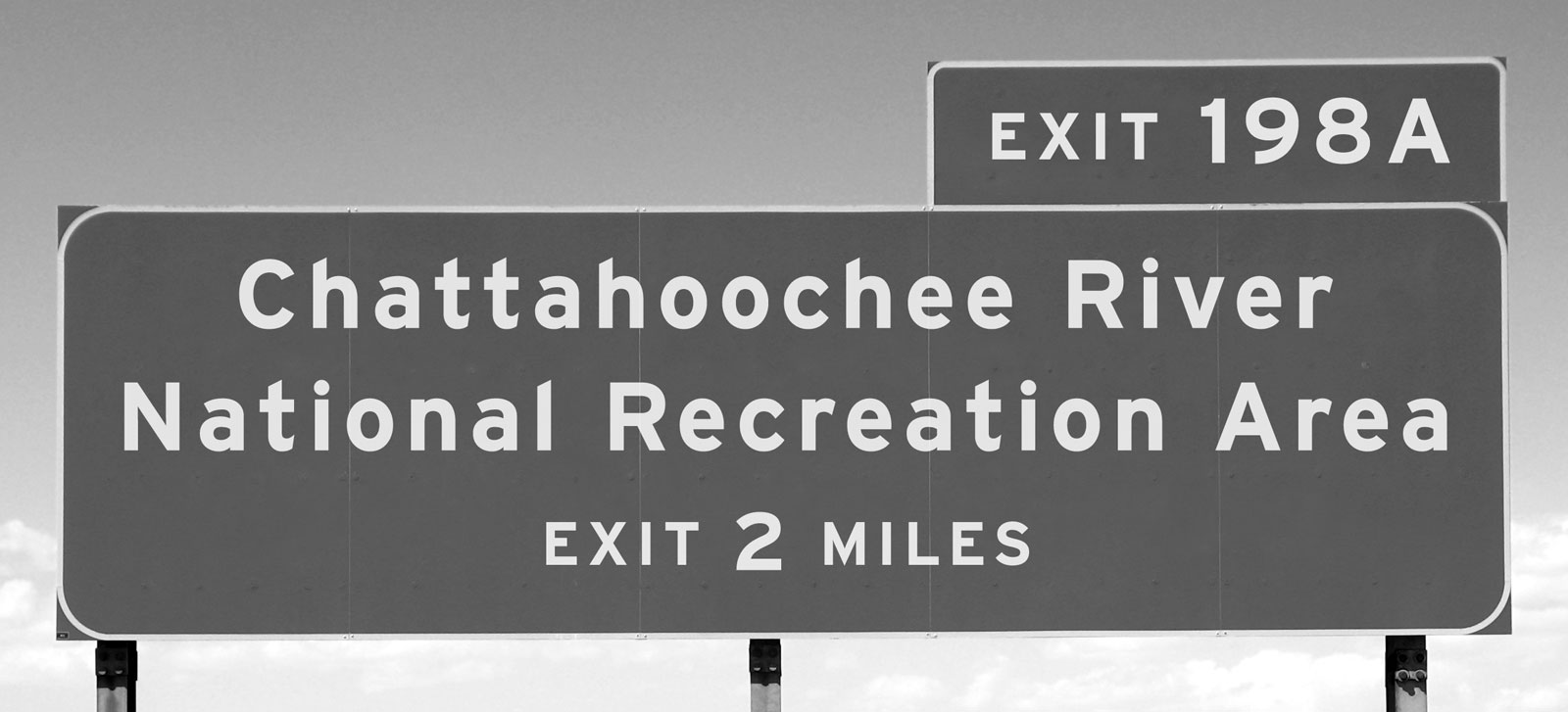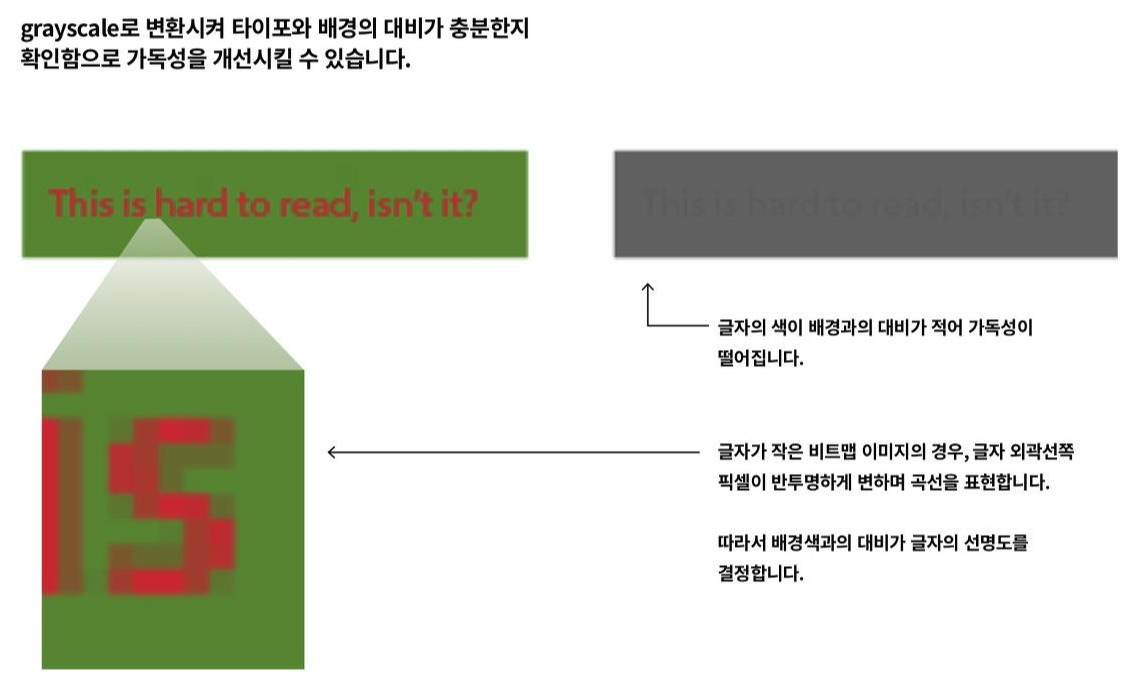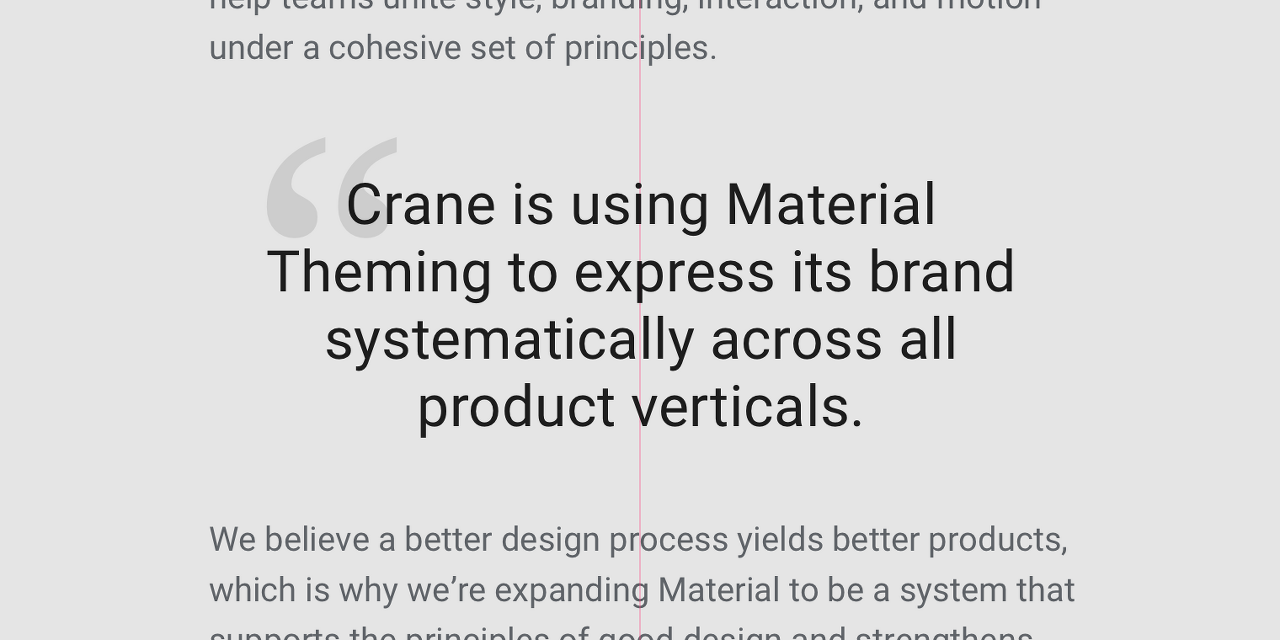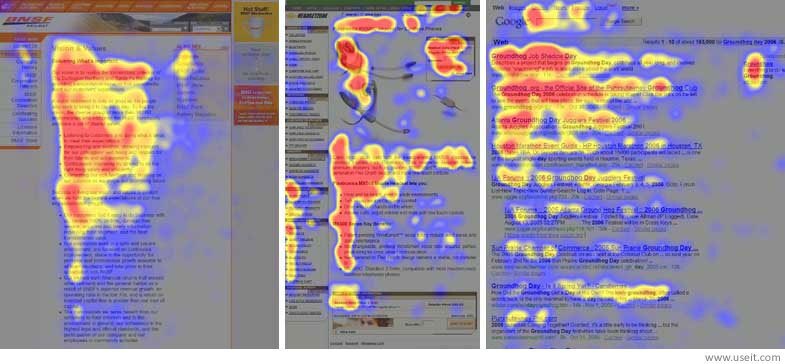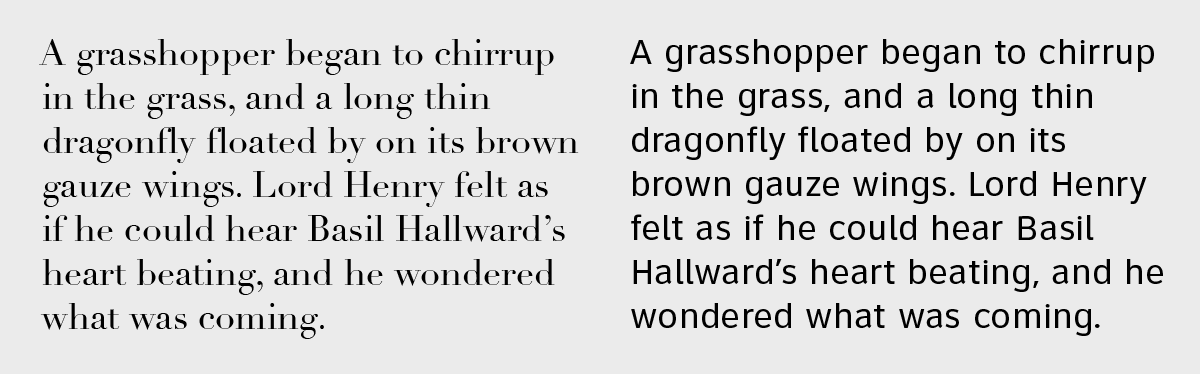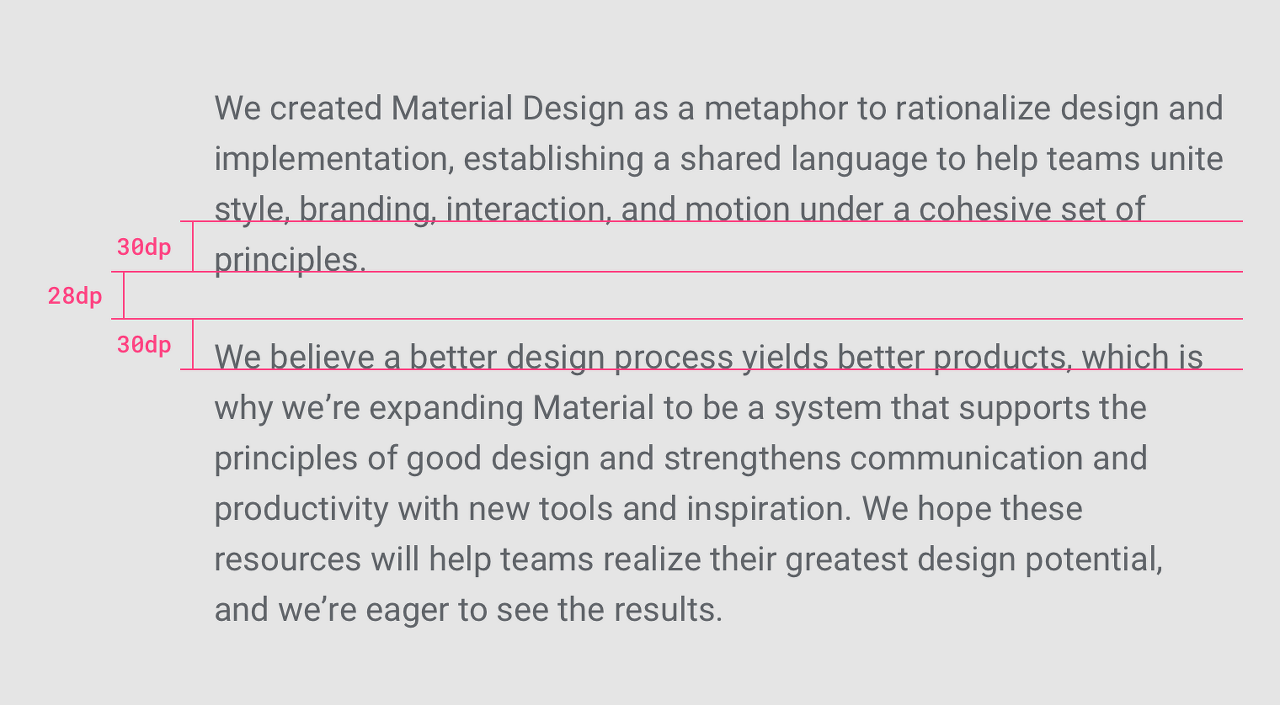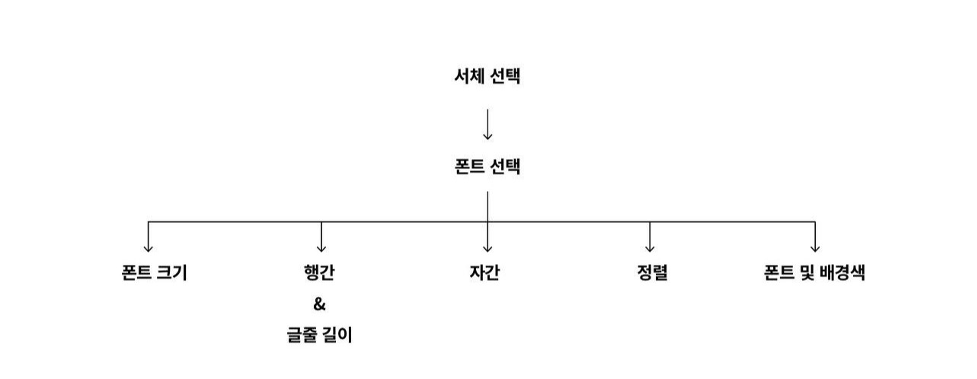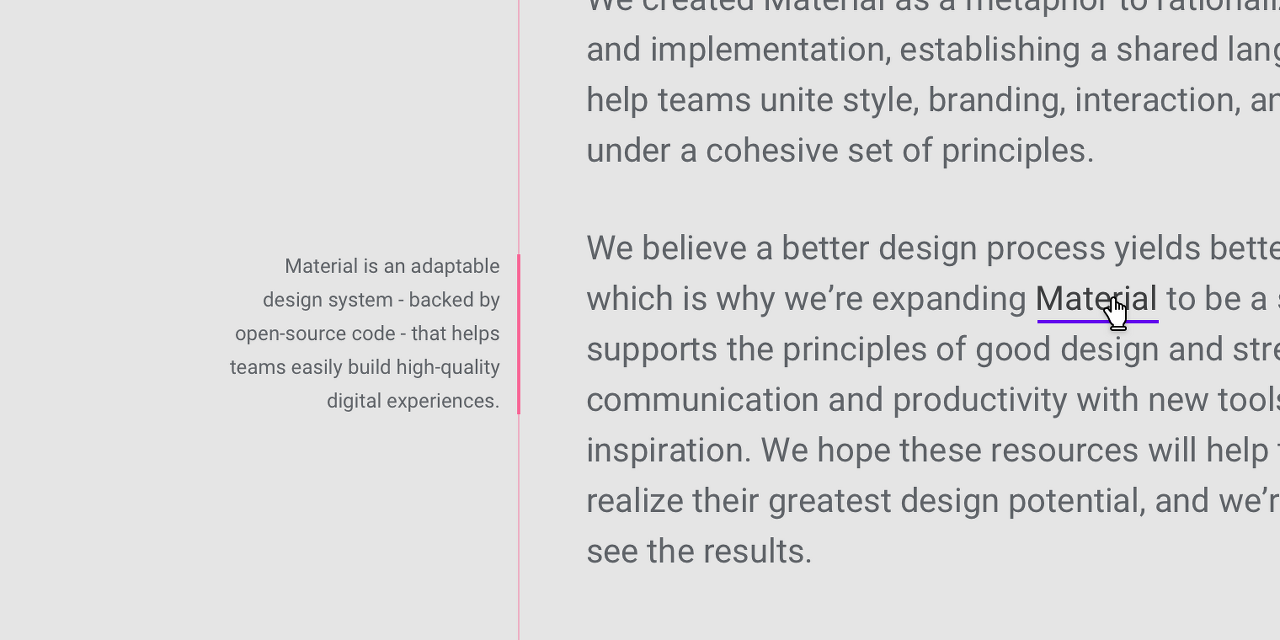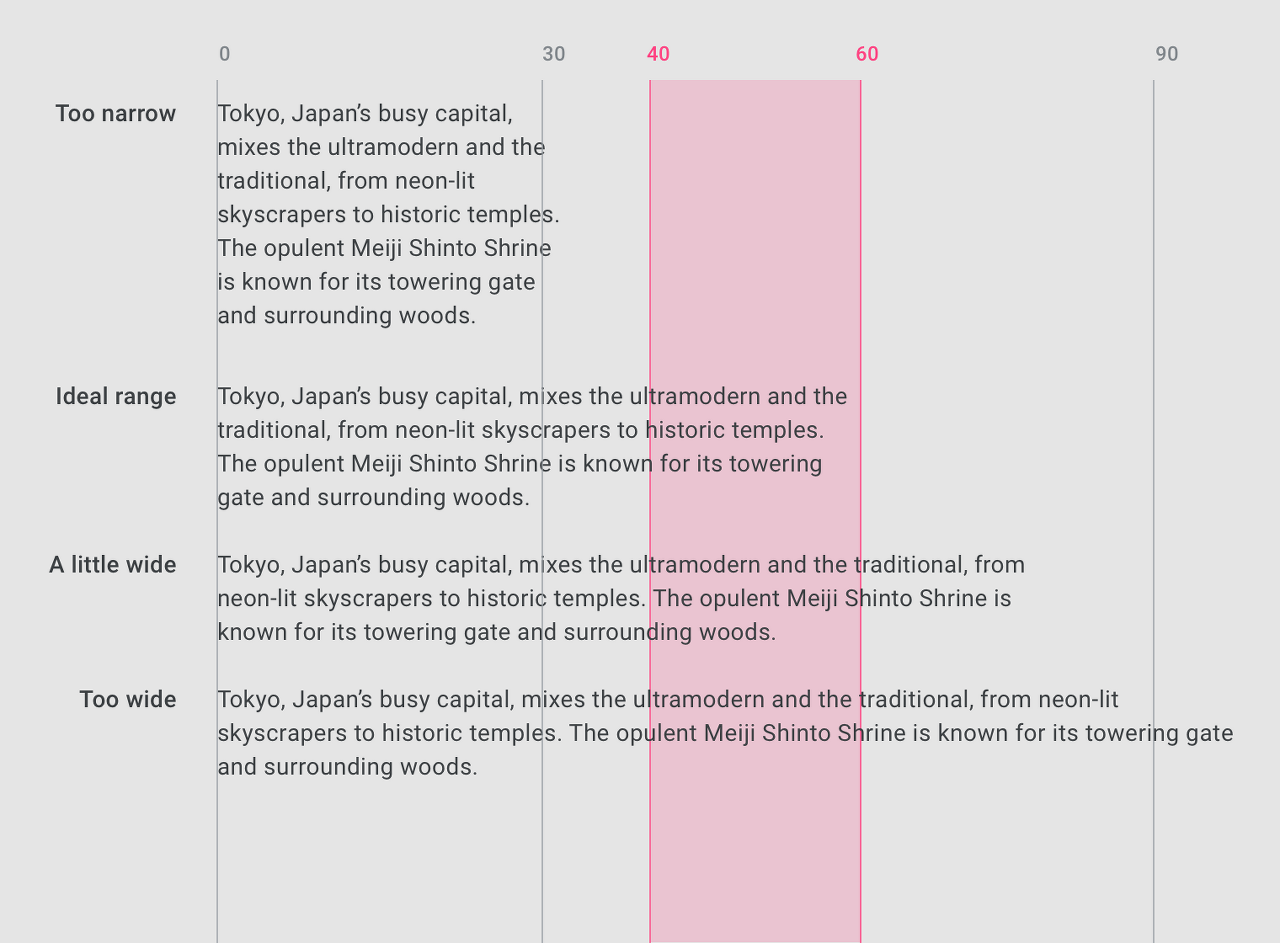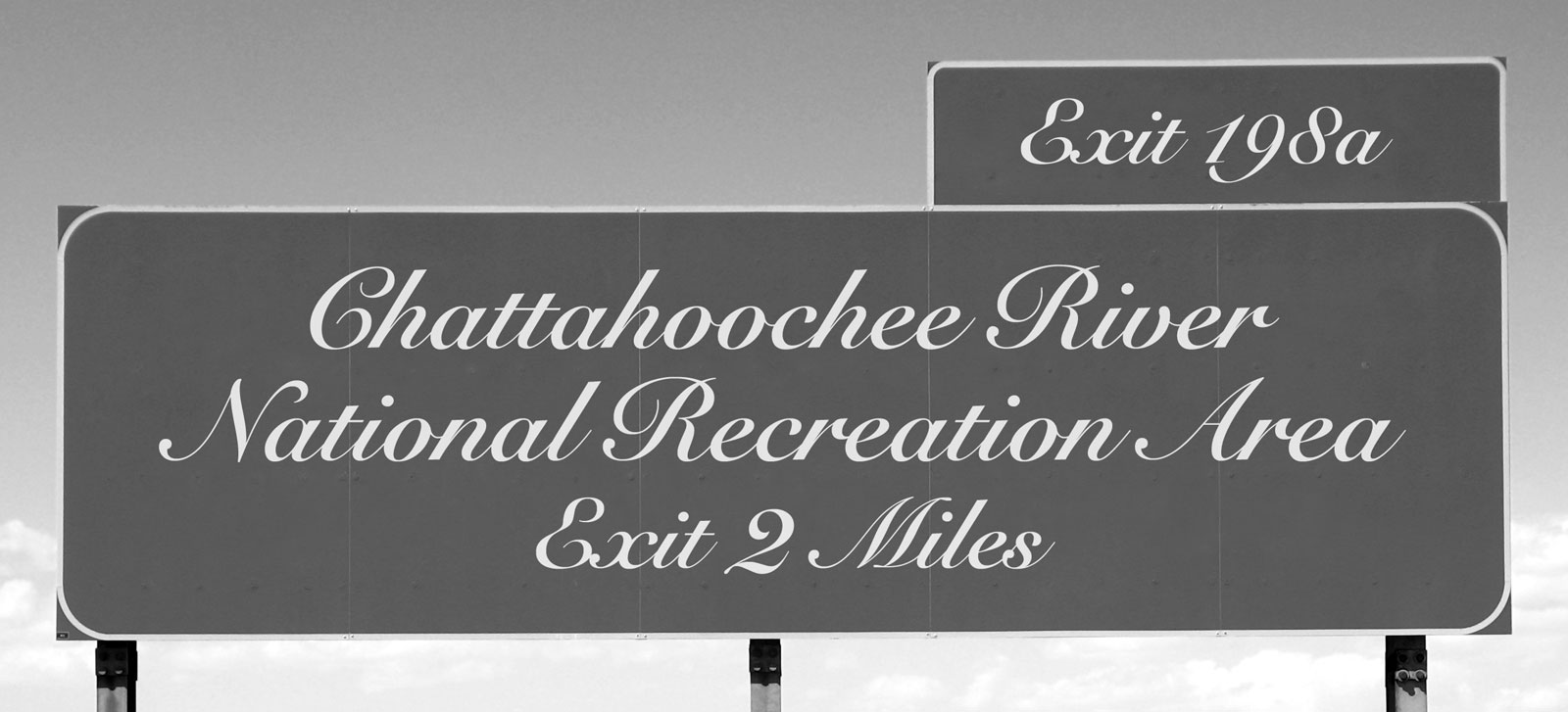
영문 타이포그래피, 실패하지 않는 법 Part.2
타이포그래피의 중요성과 활용법
지난 글에서는 디스플레이용과, 본문용으로 적합한 폰트를 고르는 방법에 대해서 알아봤는데요. 이번 글에서는 타이포그래피라는 용어가 아직은 생소한 일반인 분들과 이제 디자인을 막 공부하기 시작한 분들을 위하여 타이포그래피의 중요성과, 활용법에 관하여 집중적으로 이야기하려고 합니다.
타이포그래피, 뭐가 그렇게 중요한데?
그래픽 디자인에서 타이포그래피는 크게 두가지 역할이 있습니다.
1) 높은 정보 전달력
좋은 타이포그래피는 정보를 체계적이고 명확하게 보여주어, 사용자가 원하는 정보를 빠르고 쉽게 이해하도록 도와줍니다. 아래 교통표지판을 예로 들어볼까요?
(좌) 미국의 일반적인 교통표지판, (우) 필기체로 적힌 교통표지판
왼쪽 표지판의 경우 정보의 종류와 중요성에 따라 글자의 크기, 두께가 다르게 세팅되어 운전자가 정보를 파악하고 습득하기 쉬운 반면, 오른쪽 표지판은 읽다가 길을 잘못 들거나 어딘가를 박은 자신의 모습을 보고 있을지도 모릅니다.
2) 흥미 유발 & 집중력 증가
좋은 타이포그래피는 사용자의 흥미를 유발하고 콘텐츠를 지속적으로 소비하게 도와줍니다. 이것이 바로 타이포그래피가 편집디자인에서 가장 중요한 요소로 고려되는 이유입니다. 아무리 좋은 콘텐츠여도 읽기 불편하면 더 이상 보고 싶지 않으니까요.
전공책이 왼쪽 단락과 같은 글자로 쓰여 있다고 상상해보세요!
고려해야 할 점들.
타이포그래피를 성공적으로 사용하려면, 가독성(Readability)과 판독성(Legibility)을 필수적으로 고려해야 합니다. (흔히 영문 자료를 번역하는 과정에서 두 용어를 모두 가독성으로 오역하는 경우가 많으니 유의하시길 바랍니다.)
가독성 (Readability) : 텍스트가 얼마나 편하고 쉽게 읽히는가의 기준
판독성 (Legibility) : 글자를 인식하고 다른 글자와 구별하기 쉬운가의 기준
가독성을 높이는 방법들.
가독성은 정보 전달 혹은 오랜 집중력을 요하는 문서에 가장 필수적인 요소입니다. 가독성이 높은 글은 본문(body text)에서 정보 전달력을 높이고 글을 읽는 데 있어 집중을 도와주지만, 가독성이 낮은 글은 눈이 쉽게 피로해지고 집중력을 저하시킵니다.
1. 알맞은 서체 및 폰트 선택
프로젝트 목적에 맞는 서체와 서체 안에서 폰트를 고르는 일은 작업의 퀄리티를 책임지는 가장 핵심적인 요소입니다. 이전 글인 영문 타이포그래피, 실패하지 않는 법_part.1에서 자세한 정보를 확인해 보세요.
2. 최소 글자 크기 유의하기
항상 폰트의 최소 크기를 유의해야 합니다. 글자가 너무 작아지면 가독성이 크게 저하되며 인쇄물의 경우 잉크 번짐으로 제대로 프린트가 되지 않을 수도 있습니다.
※해결법
작업물의 일부를 샘플로 프린트해보시거나 혹은 실제 크기로 확인해 보시기를 권장합니다.
3. 자간 조정하기 (두 가지 방법)
영문 타이포그래피는 모든 글자의 간격을 일정하게 조정하는 Tracking과 두 글자 사이의 간격을 조정하는 Kerning이 있으며, 글자의 크기, 소문자인지 혹은 대문자인지를 항상 고려하면서 신중하게 조절해야 합니다.
타이틀(소문자)
글자가 커지면서 자간도 증가하기 때문에, 본문과의 조화를 위해 자간을 3~5% 줄이는 걸 추천합니다.
타이틀(대문자)
타이틀이 대문자의 경우 자간을 늘리면 좀 더 정교해 보이고 단어 간의 구분이 쉬워집니다. 추천 자간 조정은 5~10%입니다.
본문
타이틀의 자간 조정과 마찬가지로 본문은 글자가 작아질수록 Tracking 값을 높이고 글자가 커질수록 Tracking 값을 줄입니다.
Kerning과 Tracking
Tracking for Title (Lowercase)  타이틀을 위한 자간 세팅
Tracking for Title (Uppercase)  타이틀을 위한 자간 세팅
4. 행간 조정하기
행간은 줄 사이의 공간으로 너무 좁거나 넓을 경우 가독성을 해치는 주요 원인이 됩니다. 어도비 프로그램의 경우, 기본 행간이 소문자에서 ascender와 descender의 크기를 시각적으로 고려하여 폰트 크기의 1.2x로 설정되어 있습니다. Google Material Design에서는 본문의 경우 행간을 폰트 크기의 0.75x에서 1.25x로 권장합니다.
5. 글줄 길이 조정하기
단락에서 한 줄에 있는 글자 수를 일컫습니다. 기본적으로 단어 사이의 공간을 포함하여 40 ~ 60 자가 최적의 가독성 경험을 주며 이는폰트의 디자인에 따라 달라질 수 있습니다.
글줄 길이에 따라 눈이 머무는 시간을 시각적으로 표현한 그래프
글줄 길이가 길어질수록 사이트 이탈률이 크게 증가합니다.
6. 텍스트 정렬 방법
영문의 경우, 글자의 읽는 방향 때문에 특별한 디자인 의도가 없는 경우에는 항상 좌측 정렬을 기본으로 합니다.
중앙 정렬 예시
짧은 타이포그래피 요소를 시각적으로 구분하기 위해서만 사용하며 인용구를 예시로 들 수 있습니다. 문장이 2~3개를 넘어갈 경우는 좌측 정렬을 권장합니다.
우측 정렬 예시
아랍어나 히브리어 같이 오른쪽에서 왼쪽으로 읽는 언어의 경우에 우측으로 정렬합니다. 영문의 경우 노트 같은 짧은 텍스트처럼 레이아웃 안에서 구분시켜야 하는 상황에서만 우측 정렬을 사용합니다.
좌측 정렬
중앙 정렬
우측 정렬
7. 배경색과 타입 세팅
배경색은 텍스트의 자간과 행간 조절만큼이나 중요한 요소입니다.  타입 세팅 또한 배경색이 무엇인지에 따라 알맞게 조정되어야 합니다.